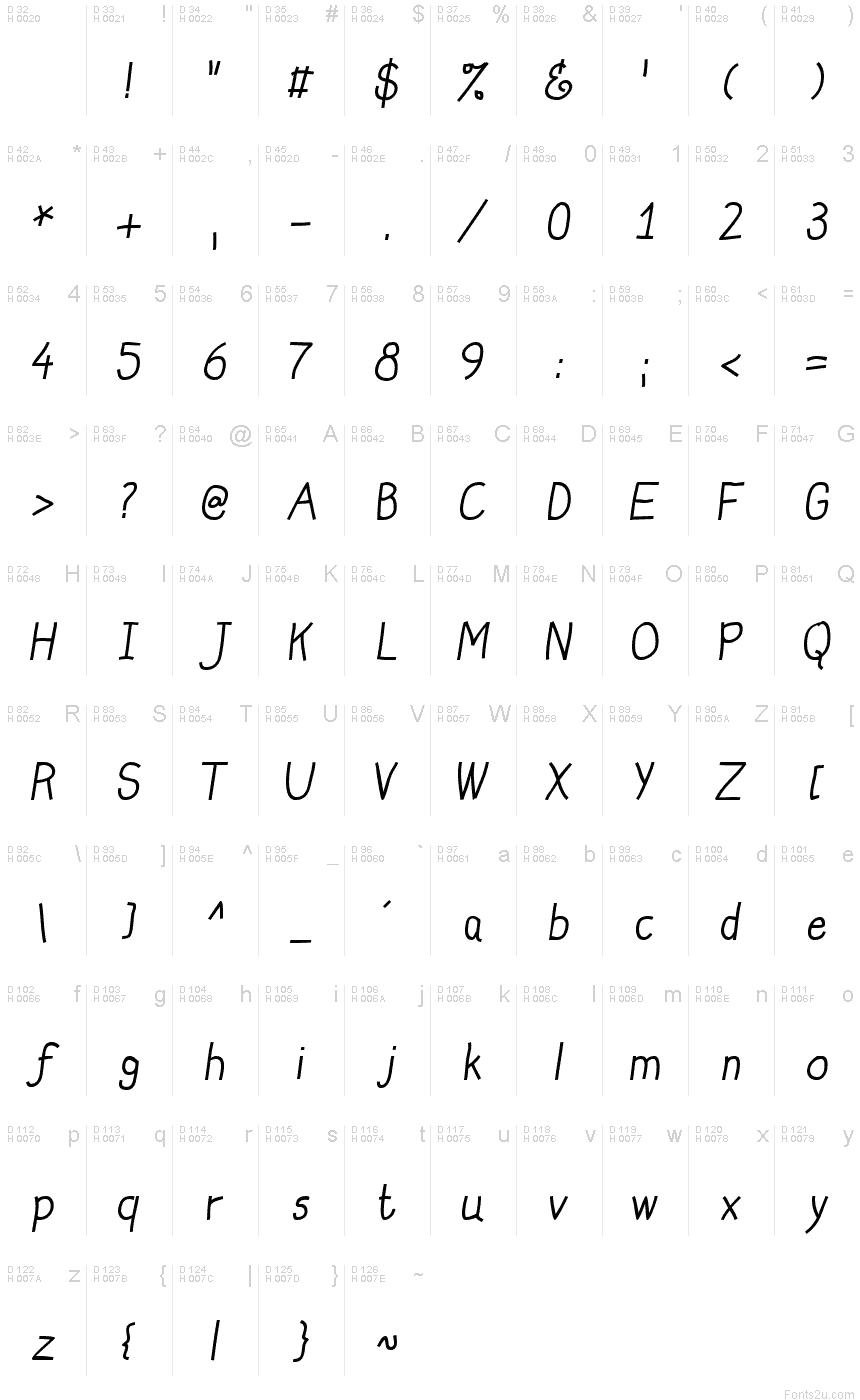
Trilok Italic di Meir Sadan è un carattere display corsivo gratuito, caratterizzato da un'inclinazione snella e modernista. Le lettere appaiono essenziali e ariose, fondendo un marcato movimento diagonale con forme arrotondate quasi geometriche; il tono generale si colloca a metà strada tra la segnaletica, il lettering per manifesti e una sans digitale delle origini disegnata a mano.
Si presta perfettamente al branding di studi di design, manifesti per mostre, titoli di riviste, titoli di testa e intestazioni web, dove la vivacità conta più della neutralità. Essendo un carattere gratuito, è ideale anche per brevi citazioni, iniziali e logotipi compatti, poiché il ritmo angolato e le curve aperte conferiscono a ogni parola una spinta dinamica immediata.